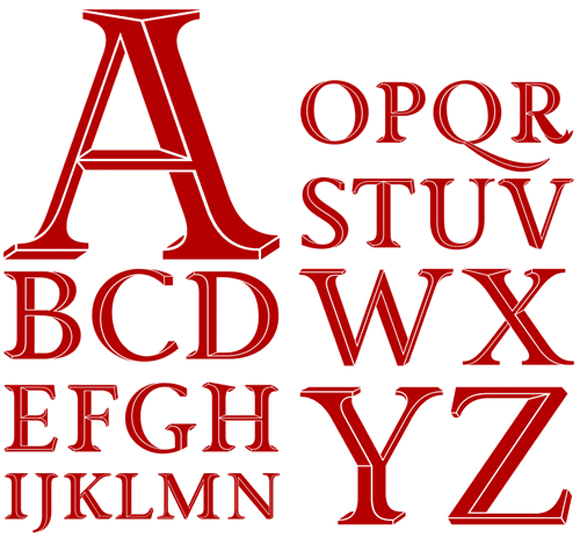
La archiconocida fundición californiana Emigre, madre de todas las madres en lo que se refiere a la historia de la tipografía digital, lanza al mercado una última expansión de sus best-sellers tipográficos. En esta ocasión, le ha tocado el turno a la famosa Priori del tipógrafo inglés Jonathan Barnbrook, diseñada originariamente en 2003 y anunciada en su momento como una “progresión” de una de las familias tipográficas más conocidas y más vendidas en toda la historia de Emigre: la Mason. Priori Acute (que así es como se denomina este nuevo lanzamiento) es el resultado de una serie de experimentos realizados por Barnbrook en el diseño de caracteres capitulares tridimensionales decorativos, inspirados en las fuentes del siglo XIX.
Sin embargo, en lugar de seguir los parámetros establecidos para el diseño de este tipo de caracteres que consiste básicamente en añadir simplemente sombras paralelas para crear el efecto de tridimensionalidad, el tipógrafo inglés ha optado por crear toda una serie de ilusiones ópticas, usando solo los cambios de dirección en los perfiles de los contornos de los diferentes caracteres (tomando como referencia el trabajo del artista gráfico holandés M.C. Escher) donde las formas resultantes son una divertida exhibición de todo un conglomerado de perspectivas incongruentes y de dimensiones variables que se interconectan unas entre otras. A primera vista y en cuerpos pequeños, el efecto óptico tridimensional es muy sutil, intentando conservar las formas originarias que hicieron famosa la familia Priori, pero cuando nos acercamos un poco más, podemos comprobar que individualmente los diferentes caracteres de Priori Acute están cuidadosamente elaborados y especialmente creados para aplicaciones selectivas como las capitulares, los titulares cortos o bien para incorporar en logotipos tipográficos.
Como elementos adicionales a la fuente, Priori Acute incluye una colección de elementos ornamentales que se pueden combinar con los caracteres capitulares anteriormente mencionados o bien entre ellos mismos, pudiendo crear una serie casi ilimitada de fondos o patrones para cualquier tipo de uso gráfico. Y tal como viene siendo habitual en todos los nuevos lanzamientos de la fundición digital Emigre, Priori Acute se puede adquirir en cualquiera de los formatos tipográficos estandarizados internacionalmente: Macintosh (Postscript), Windows (True Type) o el más reciente; OpenType.